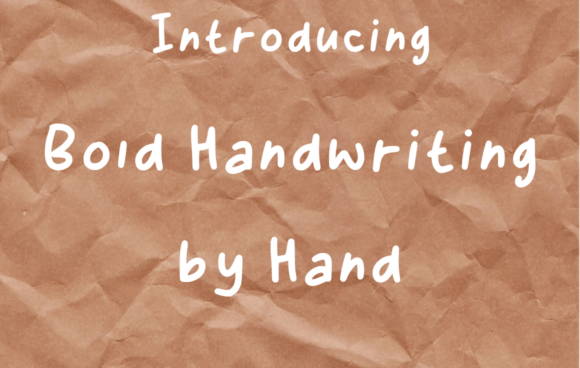
Bold Handwriting by Hand
Encontrar los elementos de diseño adecuados puede ser un desafío, pero Bold Handwriting by Hand ofrece una colección excepcional que eleva tu trabajo al instante.